Trước khi thiết kế hay thực hiện bất cứ nội dung thông tin gì, trước tiên bạn phải chọn font chữ cho mình. Tuy vậy, cách chọn Font chữ đẹp không phải ai cũng biết. Việc chọn được font chữ phù hợp thường mất khá nhiều thời gian của bạn.
Font chữ script (viết tay) là một lựa chọn font chữ đẹp mà bạn nên quan tâm trong thiết kế đồ họa. Bài viết này sẽ giới thiệu các font chữ phổ biến và được ưa chuộng nhất hiện nay.
Có bao nhiêu kiểu Font chữ?
Các kiểu font chữ sẽ chia thành ba nhóm: Script, Sans cà Serif
Script là loại những font chữ vui tươi, theo phong cách viết tay. Sans là những font chữ tròn trịa hơn, tuy vậy vẫn có những kiểu khá tinh tế. Nó cũng là những font chữ không có các dòng nhỏ được gắn vào cuối các chữ cái. Loại font chữ cuối cùng, Serif có hình dạng và kích thước khá đặc biệt, mang vẻ thanh lịch.
Vài nét về font chữ script
Font chữ kiểu script có đặc điểm là sự đa dạng bởi chúng được tạo bằng cách viết tay. Chúng thường được sử dụng trong các bản in thương mại thay cho các kiểu font cứng nhắc hơn. Có nhiều kiểu font chữ viết tay đa dạng, bởi mỗi người chúng ta thường có những nét chữ khác nhau, Tuy vậy, chúng ta sẽ chỉ tham khảo những kiểu chữ script phổ biến nhất hiện nay cho thiết kế.
Danh sách các font chữ đẹp kiểu Script
1. BIMBO
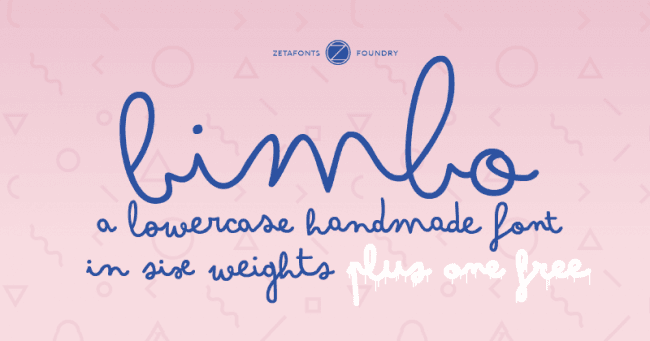
BIMBO là một font chữ đẹp theo kiểu script được thiết kế tại Zetafonts. Đây là một font chữ rất thú vị. Bạn có thể dùng nó cho tất cả các loại dự án của mình, bởi sự vui vẻ và tích cực từ nó. Font này cũng rất phù hợp với mugs và cards.
2. NEAMENTS
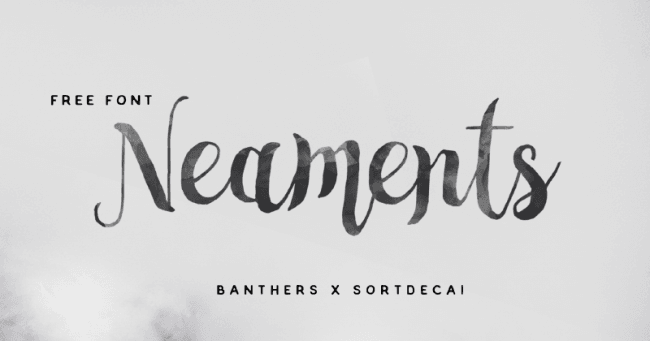
Font chữ đẹp script này được Agga Swistblnk thiết kế. Chúng có các cạnh không đều nhau, giống như cách viết của thư pháp. Nó thích hợp cho các loại dự án sáng tạo, font chữ đi kèm chữ ghép và yếu tố trang trí. Tất cả điều này sẽ tăng sự thanh lịch trong thiết kế của bạn.
3. DEBBY
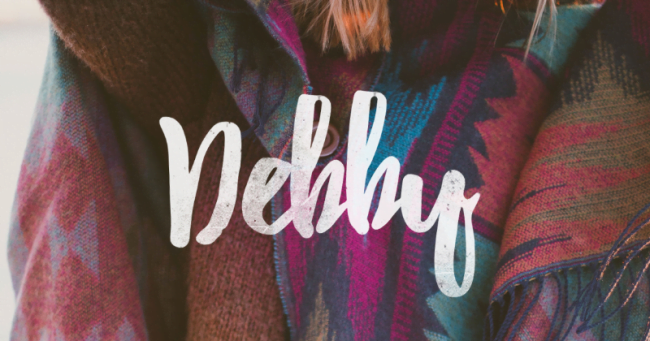
Đây là một font chữ được thiết kế bởi studio Artimasa. Nó mang vẻ nữ tính và táo bạo. Nó cực kỳ phù hợp cho các trích dẫn hoặc khi bạn muốn thêm hiệu ứng như khói chẳng hạn. Các chữ cái font này khá gần nhau, tạo sự ấm áp và tự nhiên.
4. OLIVIA
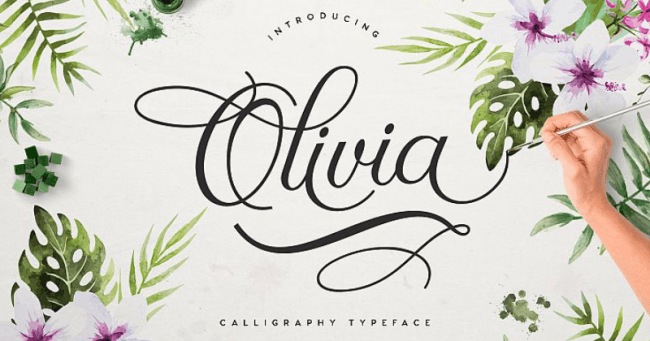
Font Olivia là một font chữ đẹp được ưa thích bởi nhiều người dùng. Đặc điểm nổi bật của nó đó là nét cọ Gradient đầy tính thanh lịch. Thông điệp phù hợp với font này thường là những ngày vui vẻ và ý tưởng mới. Nó thường được sử dung cho thiệp mời cưới hay trên các phương tiện truyền thông.
5. BALQIS
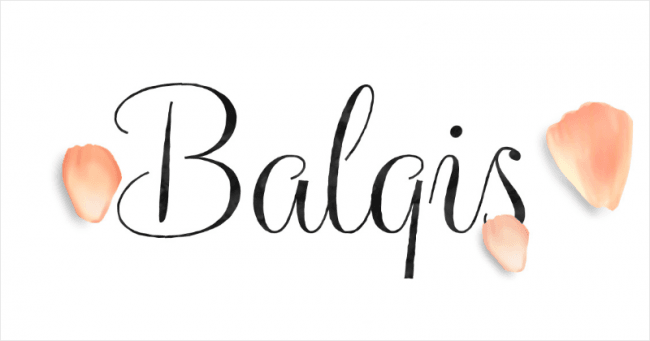
Font chữ đẹp này được thiết kế bởi Artimasa Studio. Nó là sự pha trộn giữa kiểu font a script và a sans. Đường nét của nó nổi bật ở những đường thẳng nhưng lại kết thúc với hình tròn. Font này thích hợp cho việc thiết kế các tuyên bố, bìa sách hay thiệp cưới.
6. SOPHIA
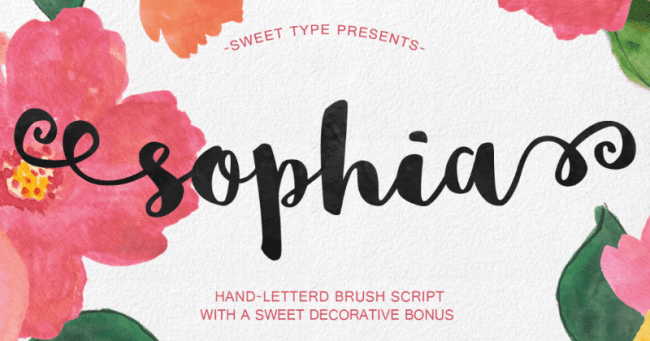
Đây là một font chữ đẹp do hai nhà thiết kế Mats và Ẹmily tạo ra. Chi tiết điểm nhấn là các xoáy và trang trí để tạo nên sự hấp dẫn hơn cho thiết kế. Sophia được đánh giá là font chữ trẻ trung, hoàn hảo cho các lời mời sinh nhật, in trên áo hay cốc lưu niệm.
7. POMMEL
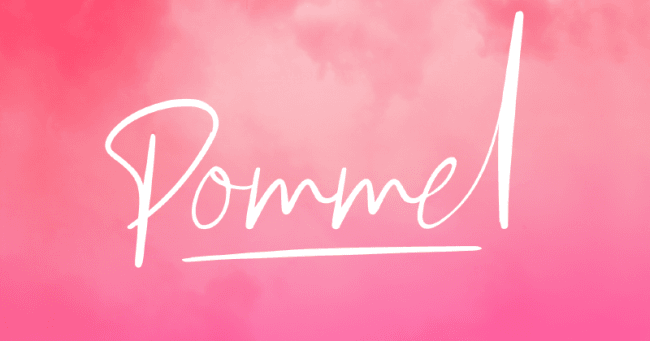
Đây cũng là một font chữ đẹp theo kiểu script. Sự kết hợp hài hòa giữa những đường nét dày và mỏng tạo cho nó sự phù hợp với các đoạn văn ngắn. Pommel nhờ đó tạo ra một hiệu ứng đặc biệt trong mắt người dùng. Đây là một sản phẩm của Craft Supply.
8. INDULGE SCRIPT
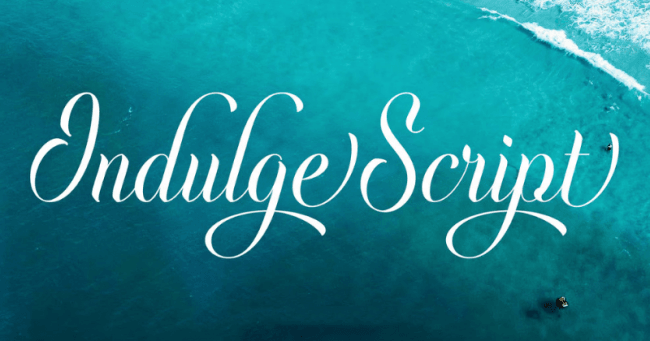
Indulge Script là một font chữ đẹp với phong cách cổ điển, xen lẫn thư pháp. Nó thích hợp trên card, nhãn và trang web truyền thống. Nhà thiết kế Anthony James cũng đã tạo ra hơn 800 đồ họa trang trí và kiểu chữ thay đổi để tạo ra nhiều sự tùy biến hơn cho người dùng.
9. BRILLIANT
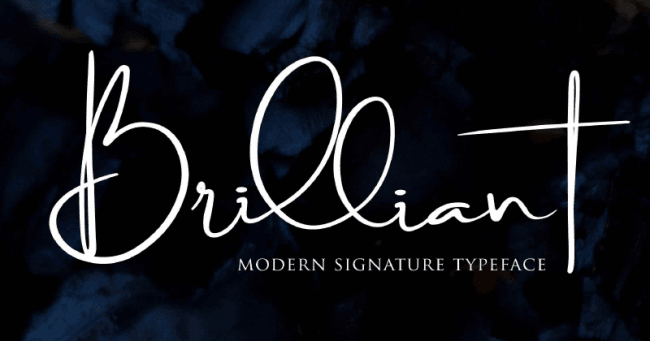
Điểm nổi bật của font chữ đẹp này đó là các vòng lặp lớn. Brilliant tạo nên sự bắt mắt và độc đáo với nhiều phiên bản vòng lặp, độ dày khác nhau. Ngoài ra còn có một số chữ ghép để làm vòng lặp tự nhiên hơn.
10. VIKSI
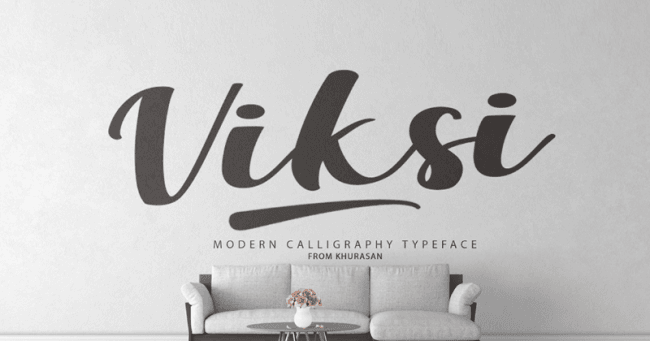
Đây là một font chữ đẹp theo phong cách Scandinavia. Nó có đặc điểm là tạo hình chữ khá dày. Điều này đặc biệt thích hợp khi bạn thực hiện các chiến dịch truyền thông xã hội hay nhấn mạnh tên các thương hiệu. Các nhà thiết kế của font chữ này – Pixelify còn tạo nên sự thích hợp cho nhiều ngôn ngữ nhằm tăng sự linh hoạt cho nó.
11. BRIGHT SUNSHINE
Đây là một bộ đôi font chữ cực thú vị. Cụ thể, một font chữ sẽ đi kèm với một cặp đôi hoàn hảo của nó. Bright Sunshine là một phiên bản kết hợp giữa font script và font serif. Nó thích hợp cho thiết kế vui nhộn và trùng lặp.
12. PHAROSI
Đây là một font chữ đẹp theo phong cách hiện đại. Đặc điểm nổi bật là tính dễ độc cũng như các chữ ghép thú vị với hiệu ứng dọc lạ mắt. Nó thích hợp cho các thiệp mời đám cưới, chúc mừng hay thương hiệu. Bạn cũng có thể thấy nó ở các tựa đề trang web hay nhãn sản phẩm.
13. SUREDER
Font chữ này thích hợp nhất cho các nhãn hiệu thời trang hoặc thiết kế tạp chí. Nó có đặc điểm chữ sẽ mềm mại và mỏng hơn tạo nên sự khác biệt.
14. MILKSHAKE
Đây là một font chữ đẹp được thiết kế bởi nhà thiết kế Laura Worthington. Font này có một đường cơ sở rất đặc biệt, chữ ghép. Nó thường được dùng cho các thiết kế đặc biệt, cần tạo sự thú vị nhất định.
15. NOELAN
Noelan là một font chữ đẹp được dùng nhiều trong các dự án sáng tạo và độc đáo. Các tên viết tắn và ký tự cuối cong mềm mại tạo sự tinh tế đặc biệt cho font chữ này.
16. BANANA YETI
Banana Yeti là một font chữ theo kiểu viết tay. Nó tạo cảm giác gợi nhớ tới nét viết cũ từ năm 1940. Đây là font chữ đặc biệt thích hợp cho phong cách cổ điển, hoài cổ.
17. BRUSHER
Font chữ đẹp này đã trở thành cổ điển trong một thời gian, tuy gần đây ít phổ biến hơn. Nó thường được sử dụng cho các loại dự án thương hiệu mang cảm giác thanh lịch, hướng tới cá nhân.
18. BEAUTIFUL BLOOM
Beautiful Bloom là font chữ kết hợp hài hòa cả phong cách thư pháp và viết tay. Với sự kết nối không đều có chủ đích giữa các ký tự, nó thích hợp cho các lời mời, logo chữ ký và thẻ cảm ơn.
19. BETTER TOGETHER
Đây là một font chữ đẹp mang đậm dấu ấn của loại font script. Các nét dày đồng đều khiến nó tạo cảm giác sắc nét hơn. Font chữ này được thiết kế bởi Mitsi. Nó thường thích hợp cho tiêu đề đồ họa, trang web với sự tươi mới.
20. KITTEN
Kitten là một font chữ hướng nhiều tới sự dễ thương và sáng tạo. Nó được lấy cảm hứng từ những con mèo xin xắn, thú vị. Nó được tạo ra bởi các nhà thiết kế tại Zetafonts. Font chữ đẹp này thường được sử dụng như một bộ sưu tập bởi tính đa dạng và độc đáo của nó.